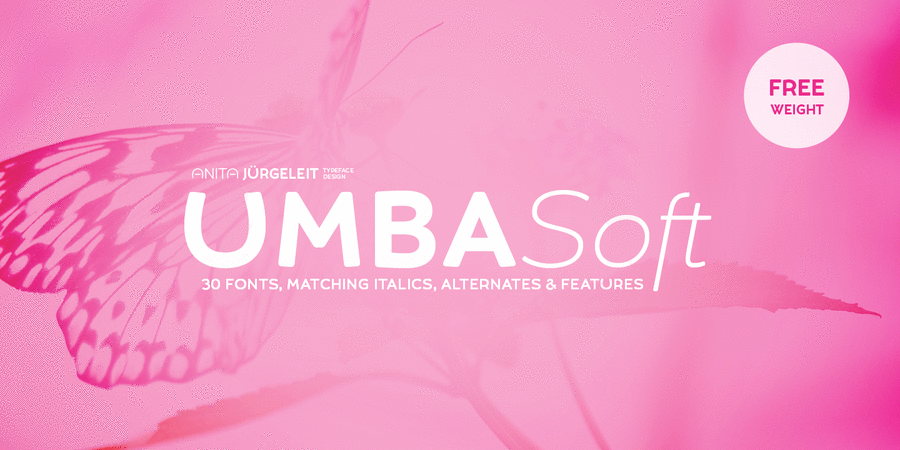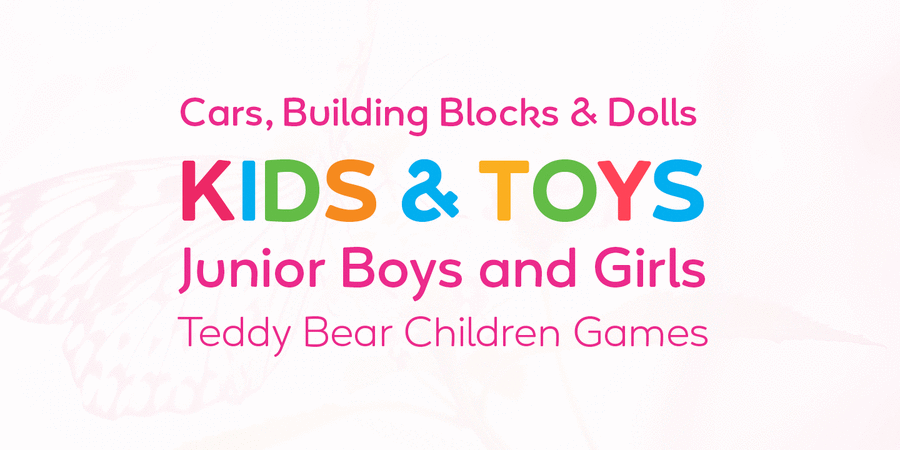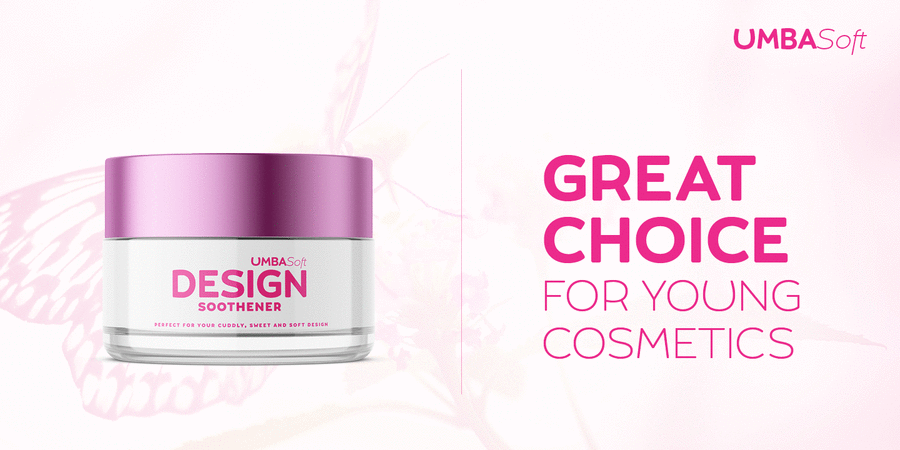
UMBA Soft – це м'який ґротеск із заокругленими кутами, який заспокоїть ваш дизайн і допоможе збалансувати текст і зображення. Вам потрібен шрифт для підліткової косметики або інших продуктів, пов'язаних з молодими людьми? Ваше творіння має бути м'яким та ніжним і вам потрібен відповідний шрифт? Щось приємне, солодке, м'яке, але з широкими можливостями серйозного шрифтового сімейства, що вирішує різні проблеми? Umba Soft – ваш вибір! Ваша типографіка значно покращиться і UMBA Soft стане вашим улюбленим шрифтом!
Тридцять накреслень з насиченостями від тонкого до жирного, плюс відповідні курсиви, допоможуть вам створити дуже привабливий дизайн. Альтернативні форми знаків і капітель доступні у вигляді наборів накреслень. Для їх використання не потрібні спеціальні програми. Накреслення з'являться в меню вибору шрифту, щоб ви завжди бачили можливості нової гарнітури.
Шрифт розробила Аніта Юргелайт в 2019 році.
Асоціації з сімейством шрифтів UMBA SoftОсобистість і характер гарнітури:
делікатний, чистий, легкий, прохолодний, тонкий, сучасний, рівний, якісний, модний, гнучкий, самобутній, оригінальний, міський, неоновий, ясний, дротяний, свіжий, лаконічний, смачний, невагомий, прозорий, інтимний, крихкий, ніжний, повітряний, худий, культурний, цікавий, характерний, М'який, приємний, комфортний, зрозумілий, симпатичний, домашній, іронічний, артистичний, виразний, яскравий, активний, грайливий, радісний, освічений, милий, Простий, неформальний, помітний, потішний, здоровий, бадьорий, сильний, доброзичливий, добродушний, добрий, круглий, щедрий, студентськиий, творчий, гумовий, важкий, літній, щасливий, гулящий, дозвільний, прикольний, пишний, затишний, гладенький, пластмасовий, рясний, насичений, спекотний, химерний, дивний, тусовочний, веселий, святковий
Місто, дієта, дизайн, АСМР, гігієна, бар, кафе, перукарня, лосьйон, краса, туалетна вода, шампунь, косметика, латте, інтер'єр, смузі, спальня, дім, вода, одяг, взуття, гра, дитяча книжка, карти, канцтовари, фломастери, мафін, чай, Хюґе, графіка, ілюстрація, небо, анімація, мультфільм, магазин, їжа, сніданок, олівці, іграшка, розваги, шоу, телебачення, дача, хенд мейд, відпочинок, фаст фуд, торгівля, школа, щоденник, м'ясо, ферма, обід, гумор, табір, гурток, розфарбування, зошит, конструктор, сир, кондитерська, солодощі, випічка, булочна, кава, жуйка, подушка, родина, вечірка, тусовка, коктейль, атракціон, свято, дискотека, аквадискотека Гарнітура має ознаки стилів:
— Гарнітура асоціюється з віком: